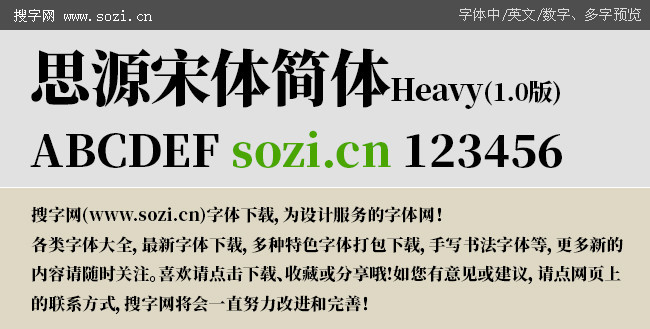
思源宋體簡體Heavy
搜字網(wǎng)提供一款思源宋體簡體Heavy中文字體下載,思源宋體是一款由谷歌聯(lián)合Adobe發(fā)布全新開源字體,是一款免費、開源宋體字體。有 65535 個字形,可共同呈現(xiàn)一致的視覺美感。本作品適用于書籍排版、報紙排版、畫冊設(shè)計,網(wǎng)頁設(shè)計等應(yīng)用。